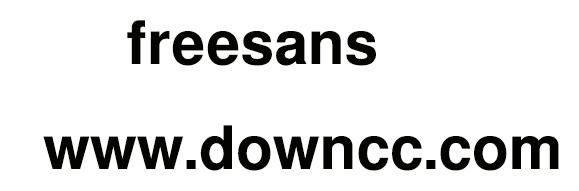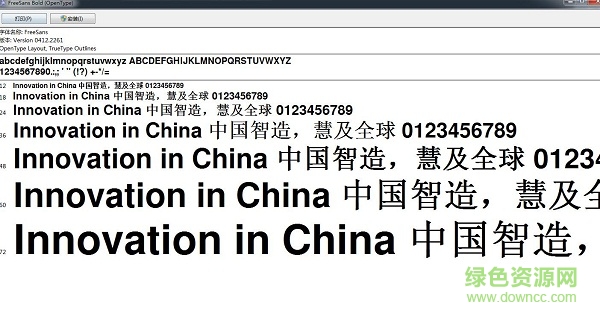
freesans是什么字體?freesans是一款無襯線字體,字體線條粗,粗細相當(dāng),韻律一致,穩(wěn)定而對稱,適合用在商務(wù)ppt、平面設(shè)計、報刊標(biāo)題等方面,歡迎大家免費下載!
英文字體特點
【字重對比】:一行字體如果其字母的筆畫字重相同,會給人一種均衡、規(guī)律并且一致的韻律。 帶給人穩(wěn)定可靠的感覺,常用于金融、安防等行業(yè),和企業(yè)logo。
【筆畫對比】:筆畫的自重發(fā)生變化的字體,將帶來一種跳躍的感覺,帶給人動感、輕松、前衛(wèi)的感覺。常用于時尚行業(yè)。